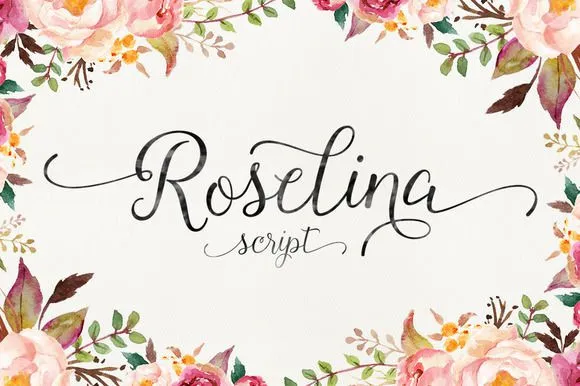
A Roselina Script é uma fonte script contemporânea com um toque vintage que combina a elegância da tipografia clássica com a modernidade do estilo moderno. Esta fonte traz à tona uma sensação nostálgica, onde a baseline flutua e se move de forma interessante, criando um ar quase mágico nas palavras escritas. Ela tem mais de 340 caracteres e oferece 105 alternativas para letras alternadas, inicial e final. Além disso, permite que você ajuste o primeiro e último caractere usando a paleta de caracteres, enquanto também alternam as swashes, os conjuntos estilizados e as ligaturas. A Roselina Script suporta múltiplas línguas, tornando-a uma opção versátil para projetos que exigem uma variedade de idiomas. Hamilton, o designer dessa fonte, soube capturar a essência da tipografia clássica enquanto mantinha um tom moderno e atual. A Roselina Script é uma ótima escolha para aqueles buscando um estilo sofisticado e elegante para seus projetos de design, seja em cartazes, gráficos ou materiais de marca. Esta fonte não apenas se destaca por sua estética única, mas também oferece flexibilidade e versatilidade, tornando-a uma opção excelente para qualquer designer que deseje incorporar um toque vintage ao seu trabalho sem sacrificar o bom design contemporâneo.